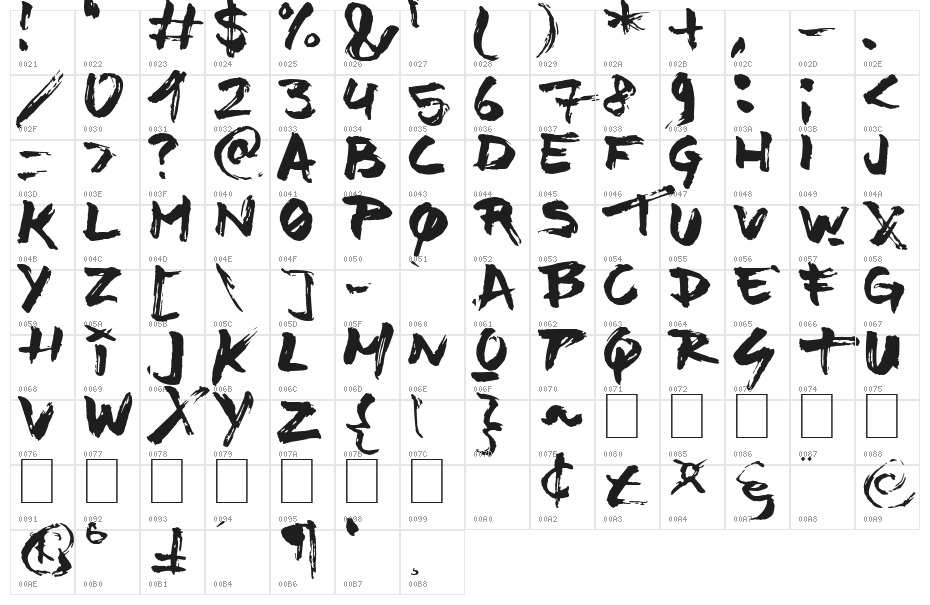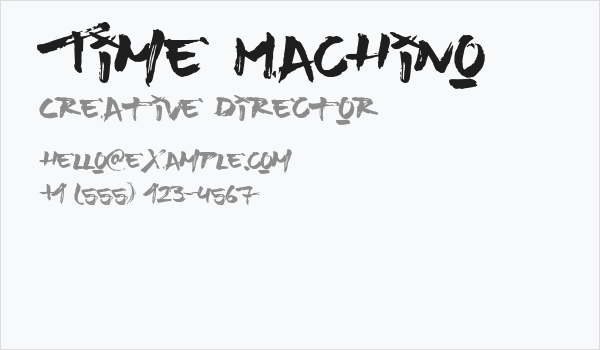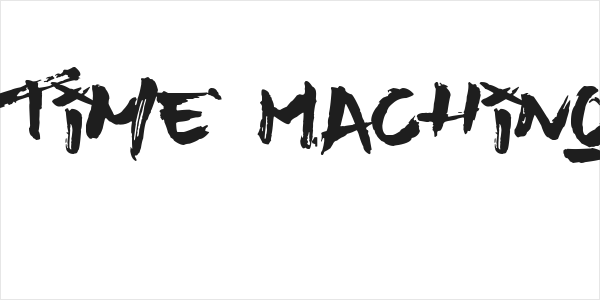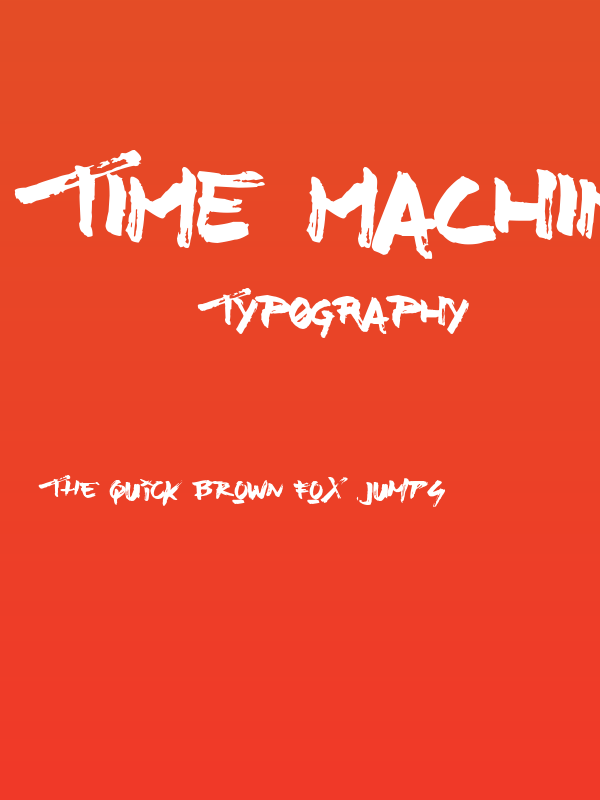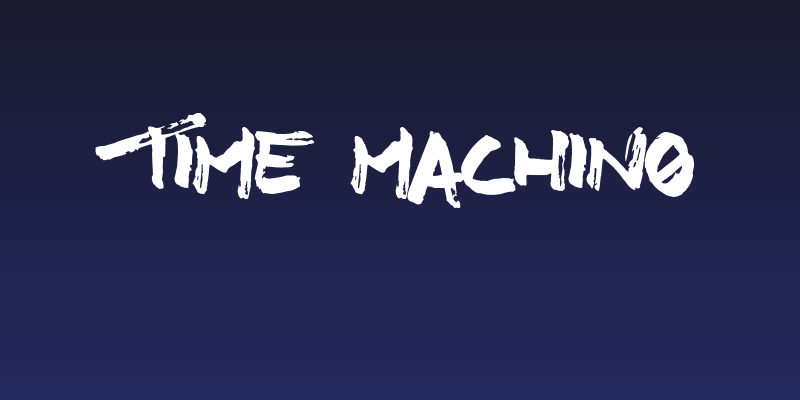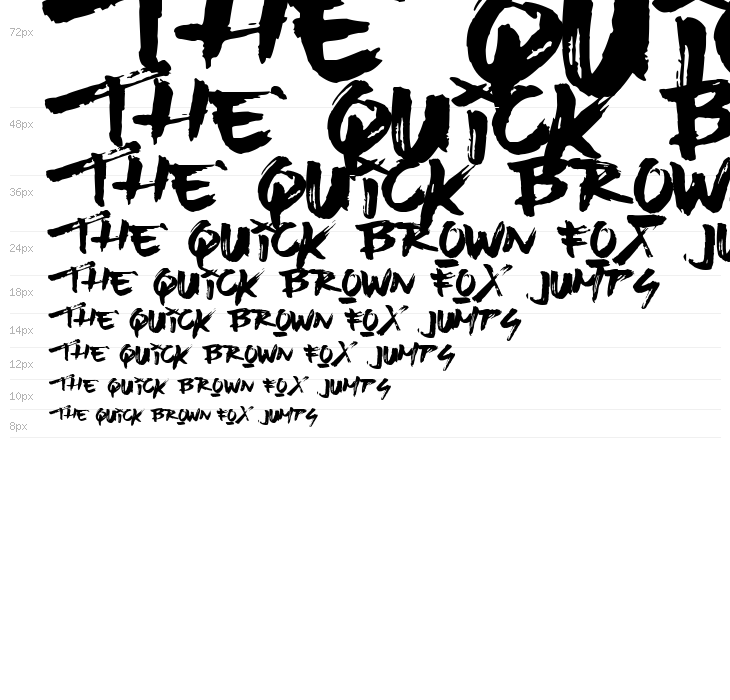
Time Machino Font
| Caso d'uso | Logos, Headlines, Artistic projects |
| Progetti proposti | Ideal for posters, album covers, graffiti art, and branding that requires a bold, artistic touch. |